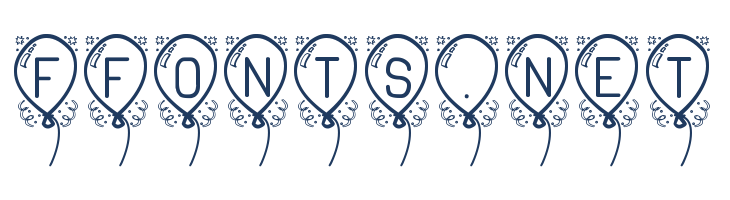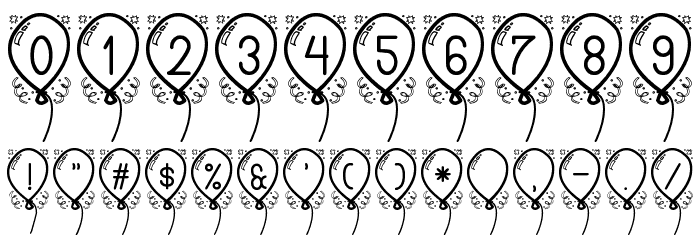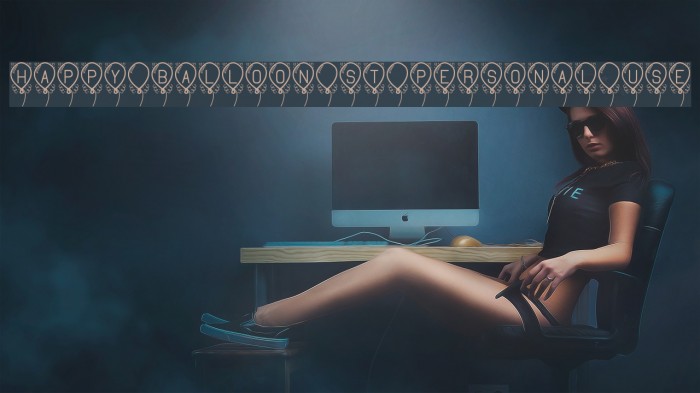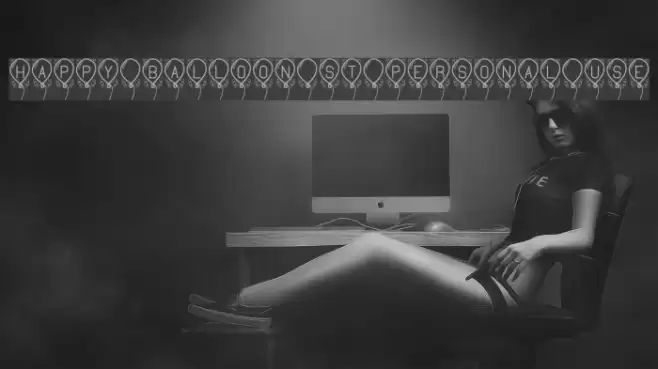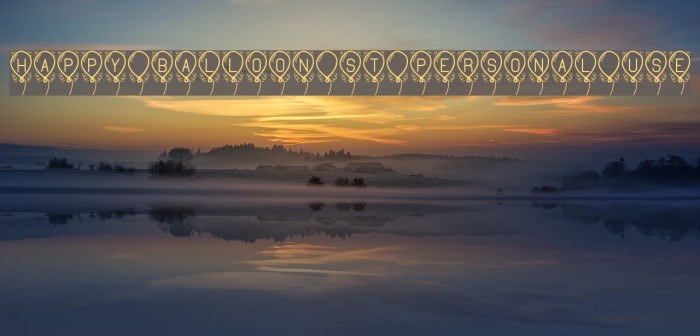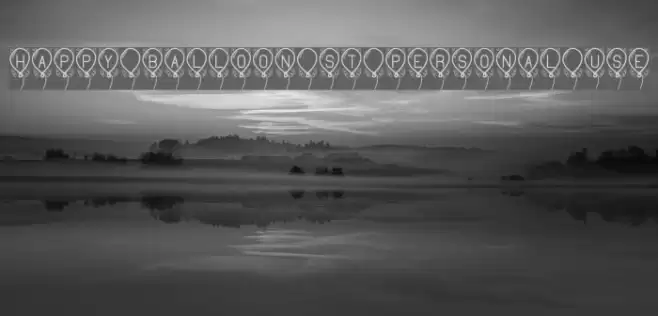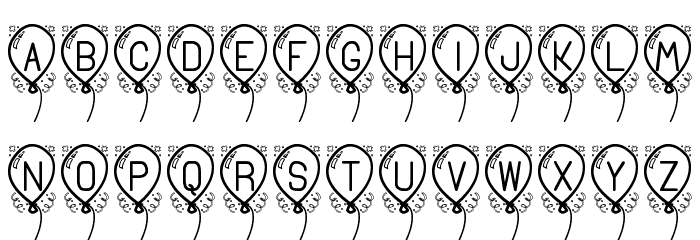
Happy Balloon St PERSONAL USE Font
| Cas d'utilisation | Headlines, Logos, Invitations |
| Projets proposés | Ideal for party invitations, children's event materials, festive banners, and playful branding. |